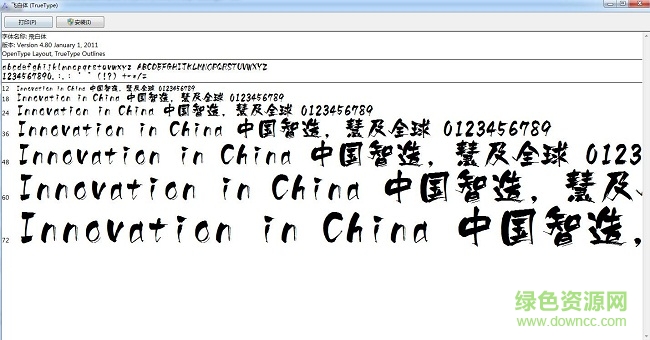
毛筆飛白字體
飛白體字體是一款帶飛白的毛筆字體,該字體蒼勁有力,線(xiàn)條伸展,飽滿(mǎn)有型,非常漂亮,可以用在藝術(shù)作品封面或海報(bào)設(shè)計(jì)中,喜歡書(shū)法字體的朋友快來(lái)綠色資源網(wǎng)下載吧!
飛白體介紹
飛白是書(shū)法中的一種特殊筆法,它的筆畫(huà)有的部分呈枯絲平行,轉(zhuǎn)折處筆畫(huà)突出,在書(shū)寫(xiě)中產(chǎn)生力度,使枯筆產(chǎn)生"飛白",與濃墨、漲墨產(chǎn)生對(duì)比,以加強(qiáng)作品的韻律感和節(jié)奏感。
毛筆飛白字體
毛筆飛白字體賞析
趙孟頫的飛白清麗秀逸,
米芾的飛白痛快淋漓,
懷素的飛白瀟灑自如,
王獻(xiàn)之的飛白顧盼生姿,
王羲之的飛白楚楚動(dòng)人,
歐陽(yáng)詢(xún)的飛白嚴(yán)謹(jǐn)險(xiǎn)勁,
顏真卿的飛白酣暢純厚!